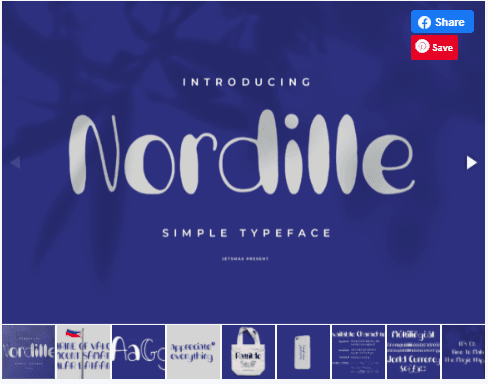
Nordille Font
Nordille - симпатичный, простой и немного необычный дисплейный шрифт. Независимо от того, используете ли вы его для дизайна, связанного с мультфильмами, детских игр или просто для любого творения, требующего изящных штрихов, этот шрифт будет отличным выбором.